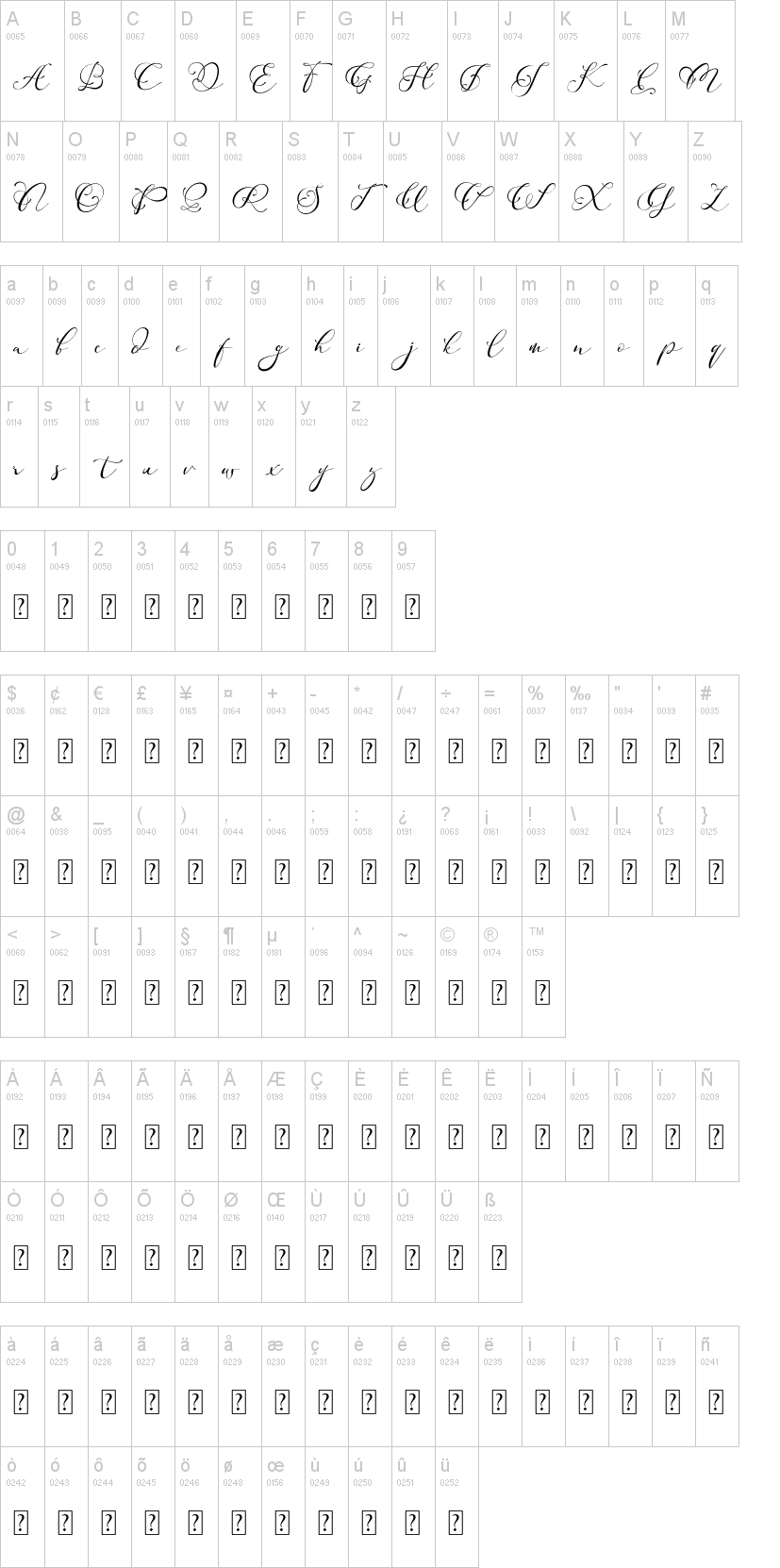
Adonessia 是一种漂亮的手写风格字体,由设计师 Gilar Studio 制作。该字体采用了一种流畅的笔画和优雅的连接,使其在设计中特别受欢迎。Adonessia 字体包含多种字重和斜体版本,适合用于设计卡片、海报、包装、书籍和网站等各种项目。 Adonessia 字体的特点之一是它的连笔,这使得它的字形之间流畅连接,看起来非常自然。此外,该字体的线条柔和,非常适合用于传达柔和、优雅和女性化的感觉。Adonessia 字体的字形已经被优化,可以很好地在印刷和数字环境中使用。 总的来说,Adonessia 是一款优雅、流畅、精美的手写风格字体,非常适合用于各种设计项目。内容介绍
Adonessia是一款非常不错的手写艺术字体,具有很好的视觉感,适合于文化类的宣传设计、商业类品牌的广告和产品包装设计以及个性化文字排版等较多场景。